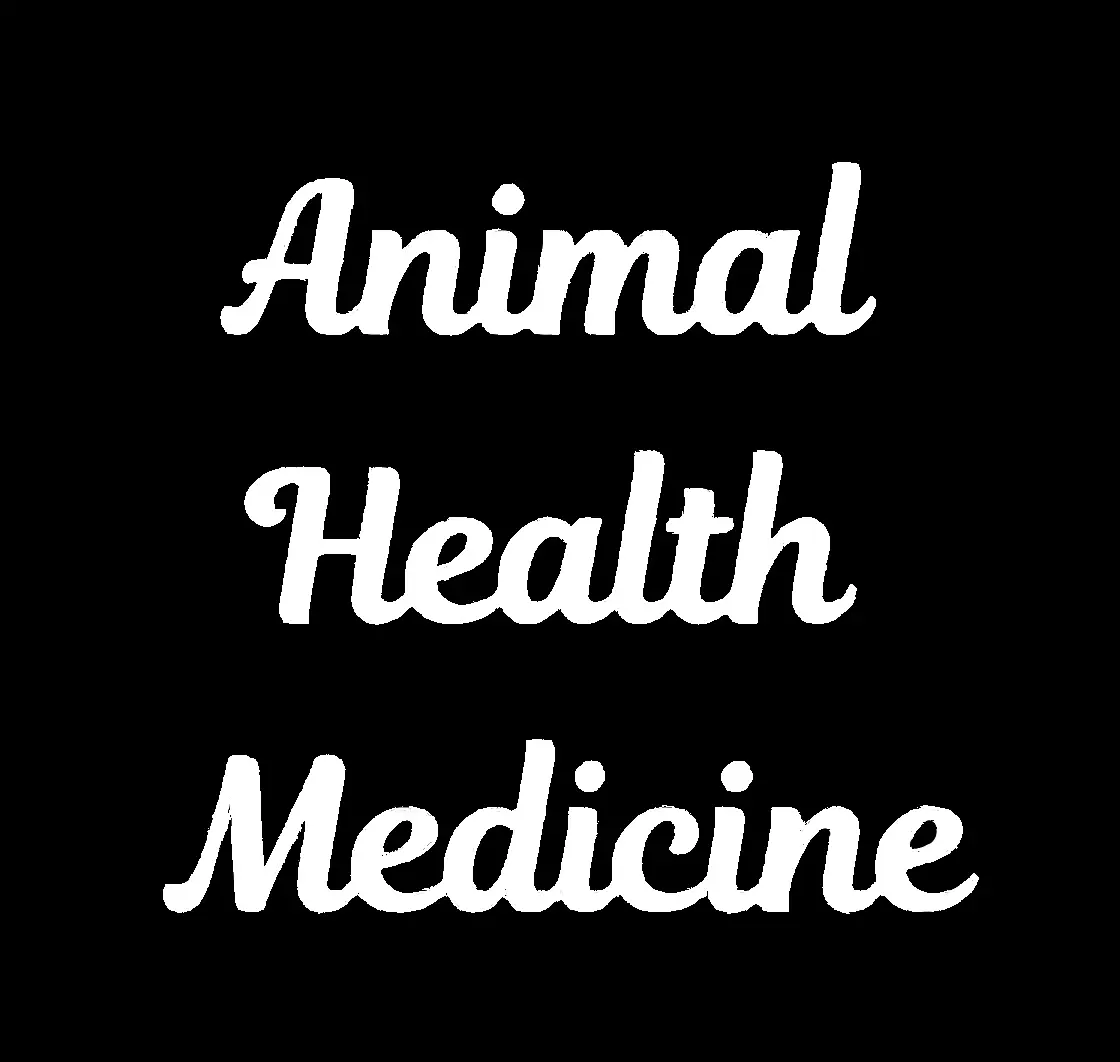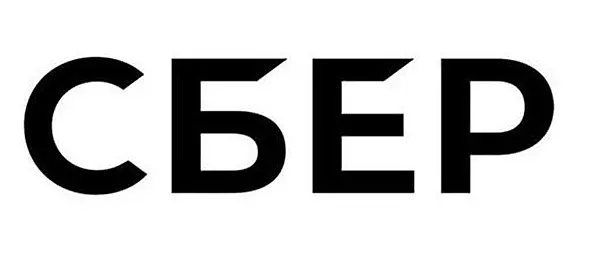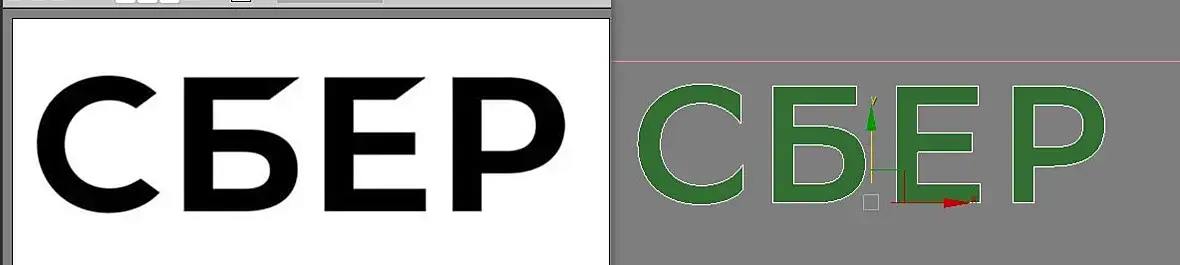
Ищу шрифт
Привет. Ищу шрифт вот такой или похожий.
TT Polls Script Bold
Привет, всем. Ищу вот еще такой. Поисковики шрифтов либо пишут всякую ерунду, либо не понимают кириллицу
По-моему это стандартный шрифт изменённый дизайнером, его никто не делал в расширение.
а вдруг
Ну по идее Сберу шрифты ваяли в Паратайп : SB Sans Display и прочие, но там начертание немного другое - может для только лого буквы обрезали?
Ну да, SBSansDisplay-Semibold более менее похож. Спасибо.
Скорее всего, это свой корпоративный шрифт Сбера.
Да мне хотя бы похожий. Надписи им на их стеклах наделать.
Женька, Тут бренд бук, как я понимаю.
Как я понимаю это их шрифт созданный для фирменной айдентики, вряд ли он есть в общем доступе, плюс ко всему я думаю он лицензионный и лучше не стоит его где-то размещатьsmiley-sorry.gif